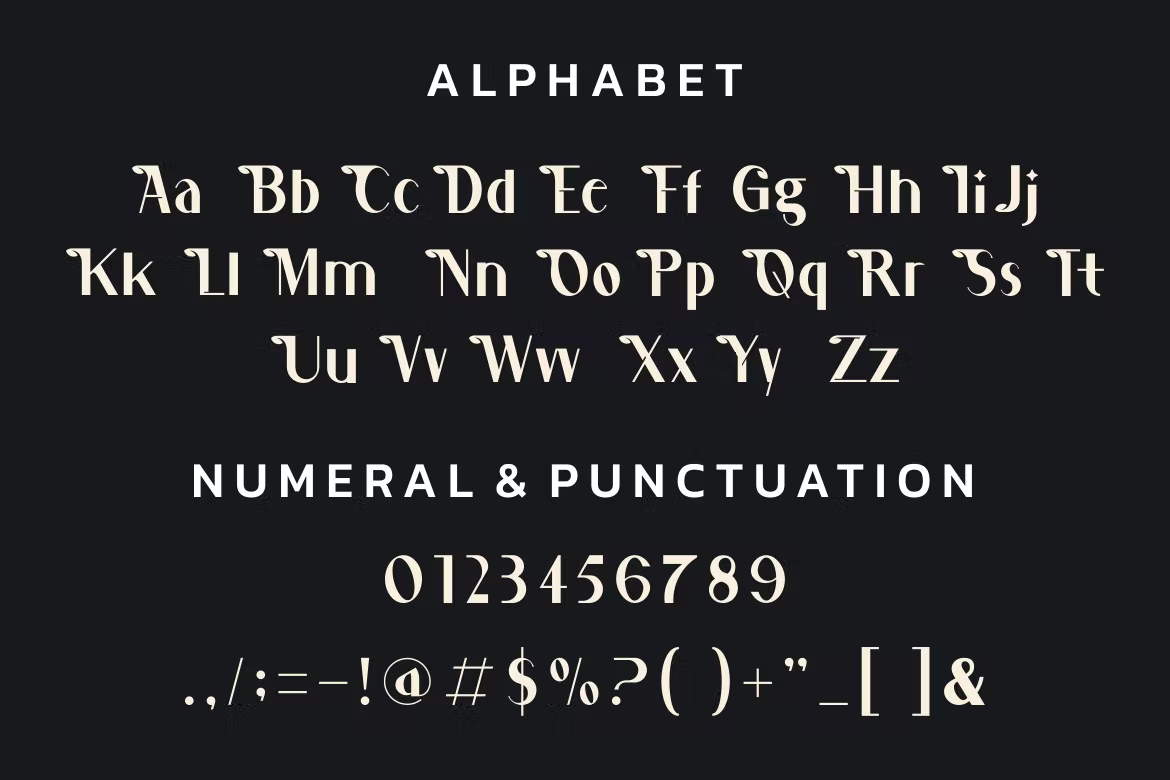
Holicho Font
Description de Holicho Font
Présentation de notre nouveau produit Holicho Font – Modern Font Holicho Font** – Modern Font est une police d’affichage audacieuse et authentique. La police convient à tout projet de marque comme un logo, l’impression de t-shirts, un produit et bien d’autres. exceptionnel dans un large éventail de contextes.